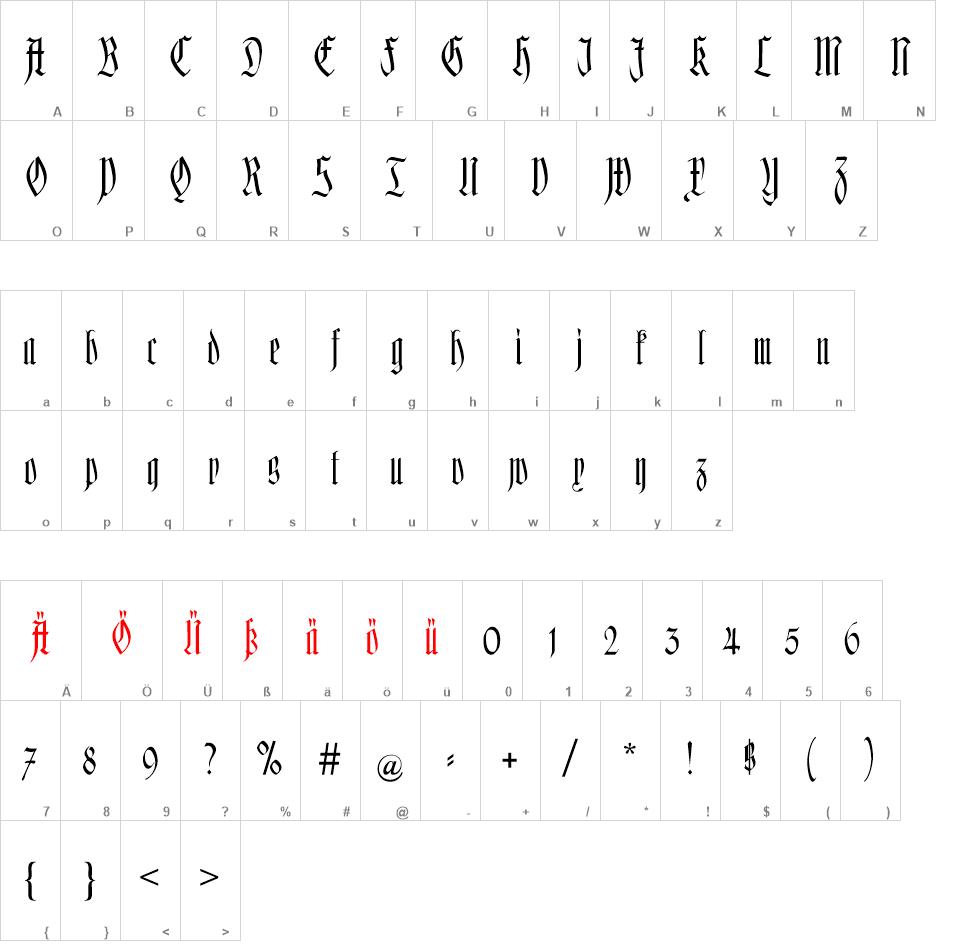
Hofstaetten
Auf Wunsch eines österreichischen Feuerwehr-Hauptmanns habe ich nach der Anschrifdt am Feuerwehr Rüsthaus aus dem Jahr 1930 diese Schrift nachgebaut, un das Haus wieder wie damals zu beschriften. Da die Original-Schrift aber ein par unübliche Besonderheiten aufweist, ist einbe zweite, etwas entschärfte Version entstanden. Beide sind wie alle meine neueren Frakturscxhriften mit einem großenb Satz Ligaturebn versehen.